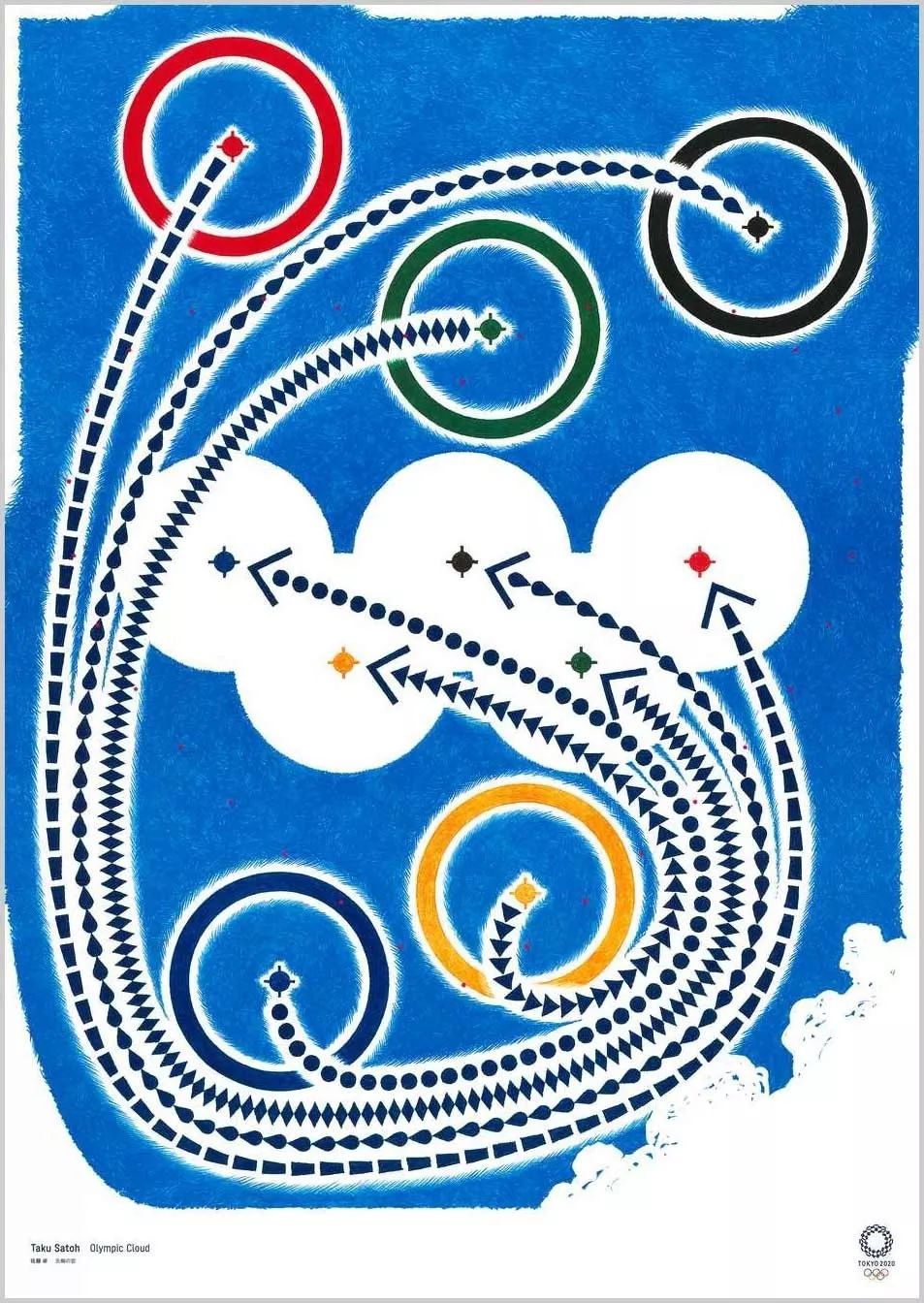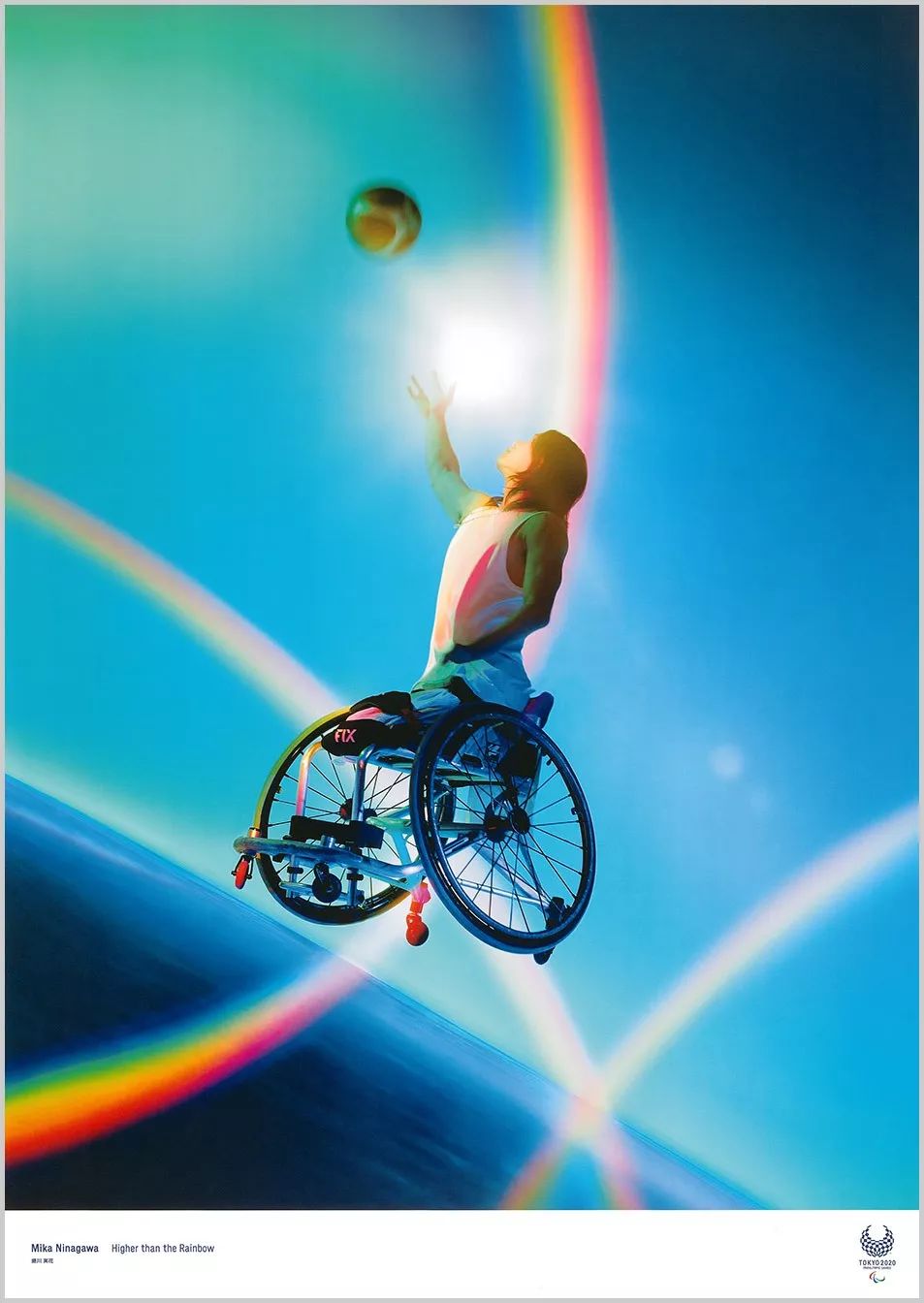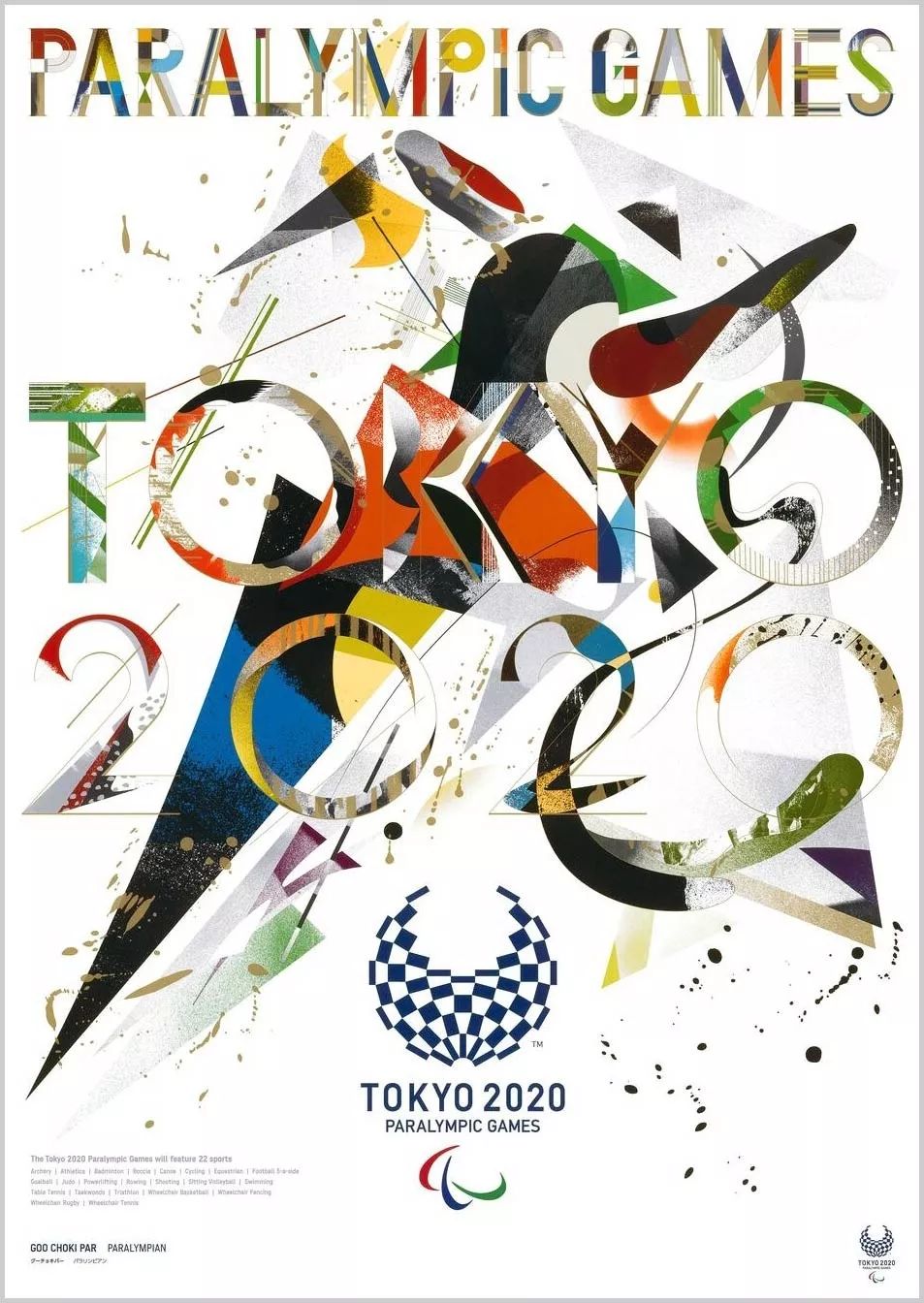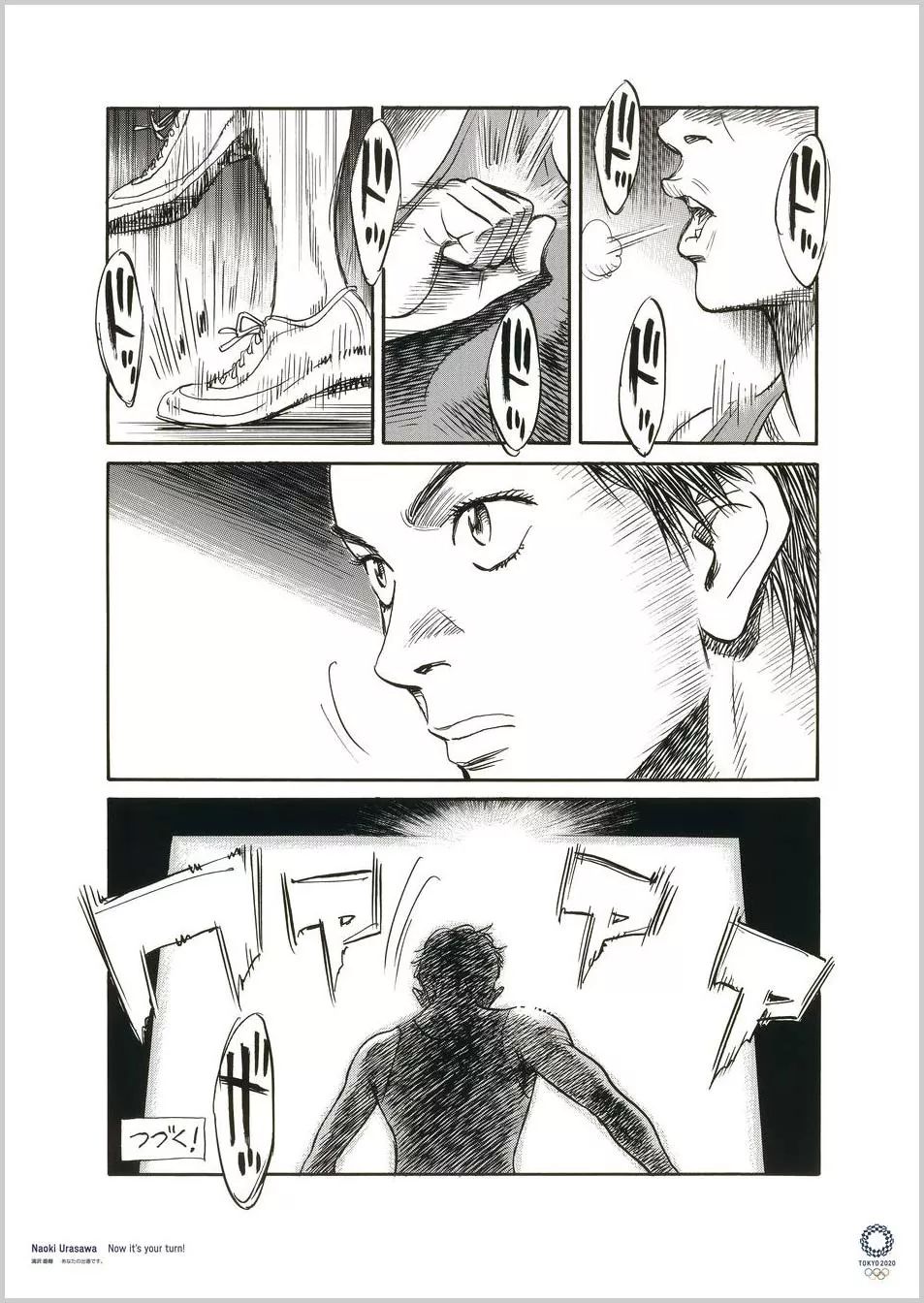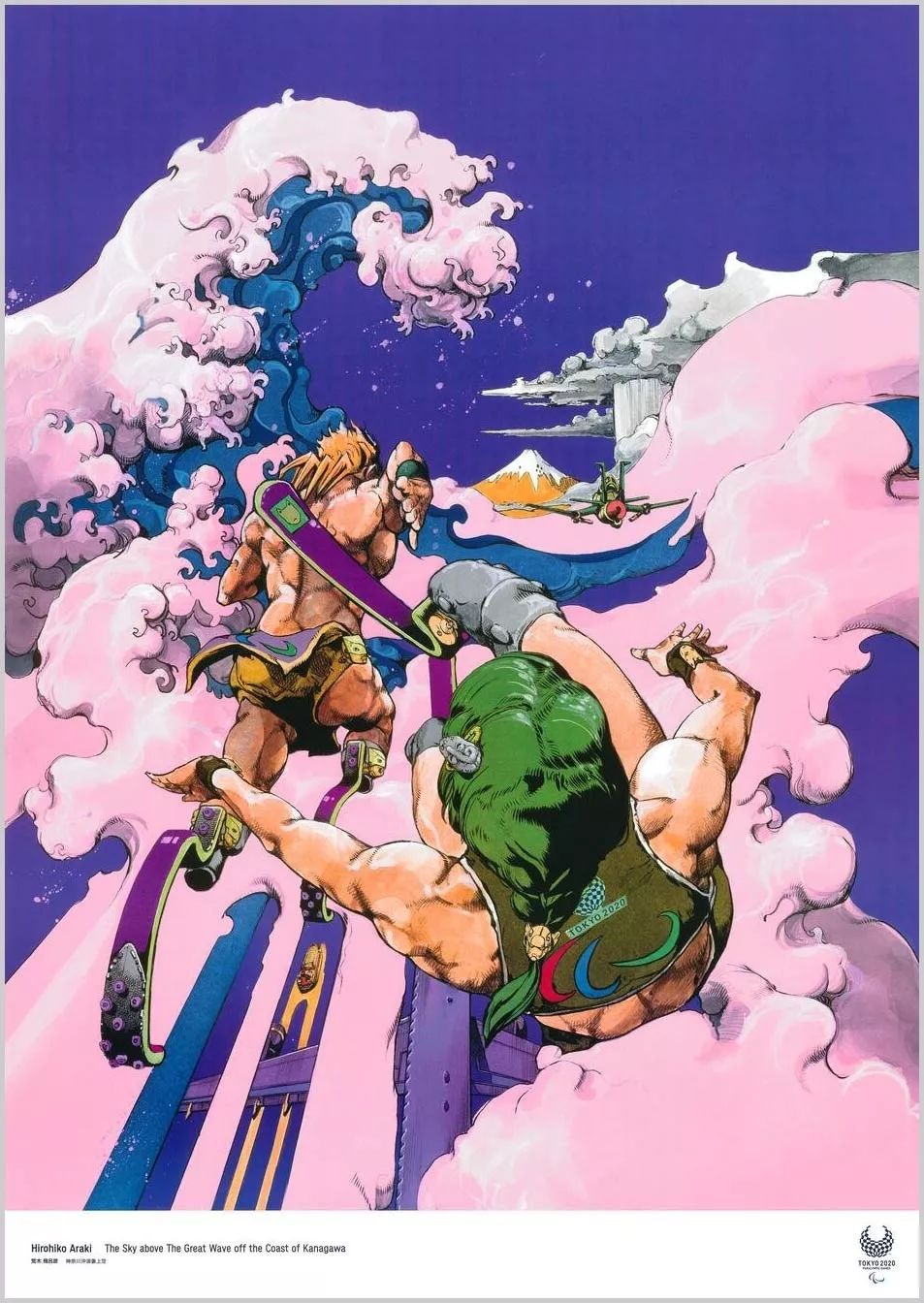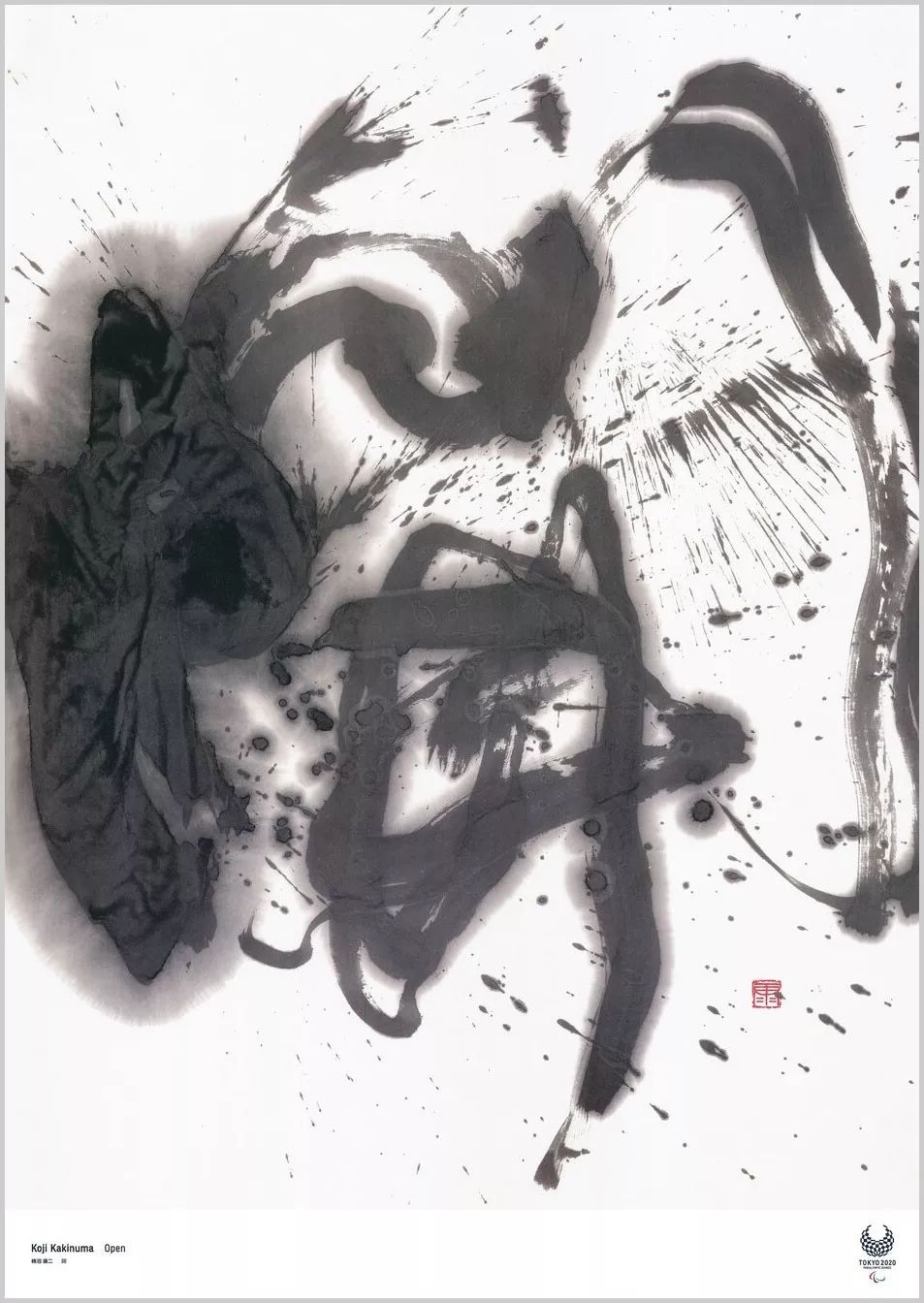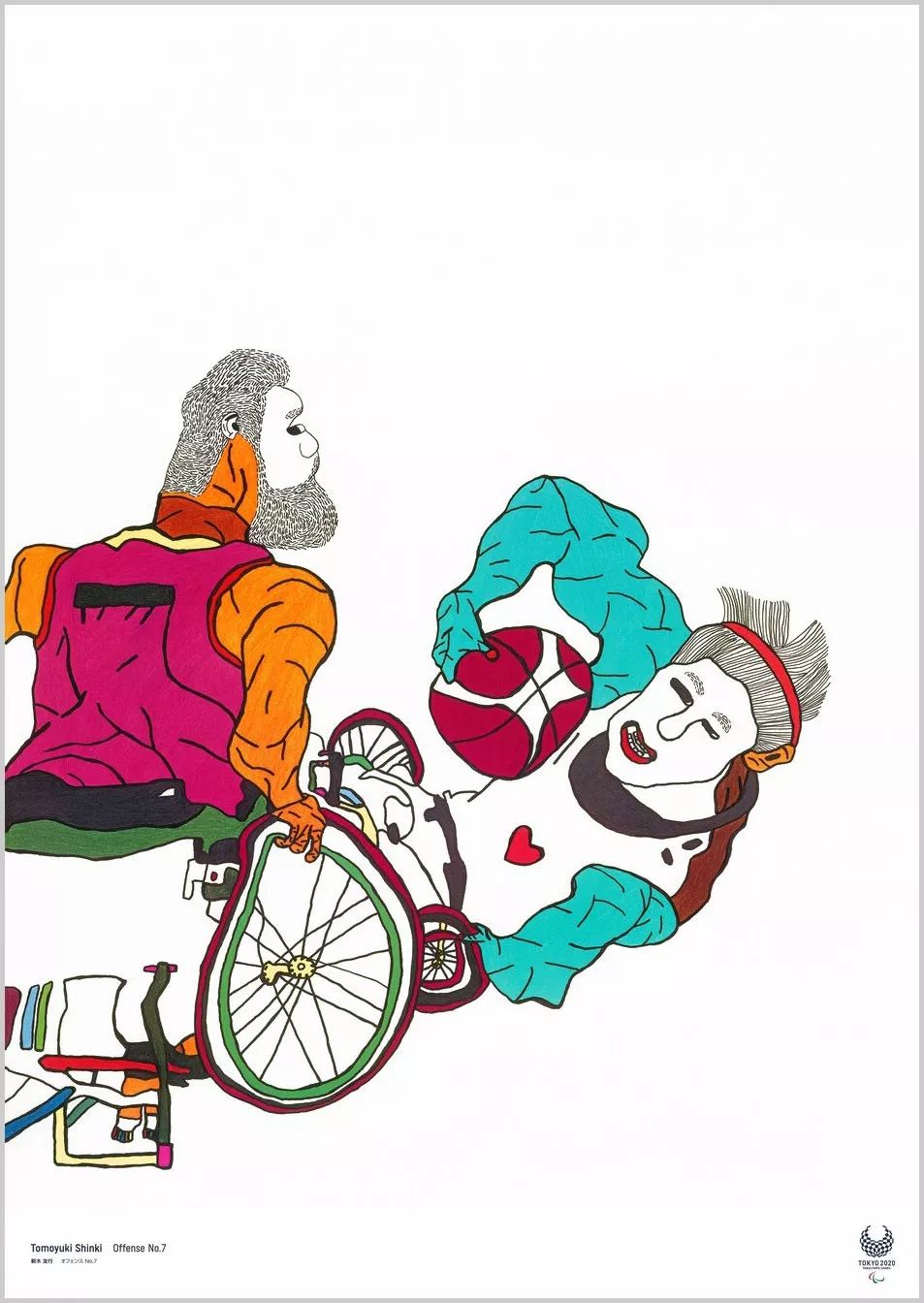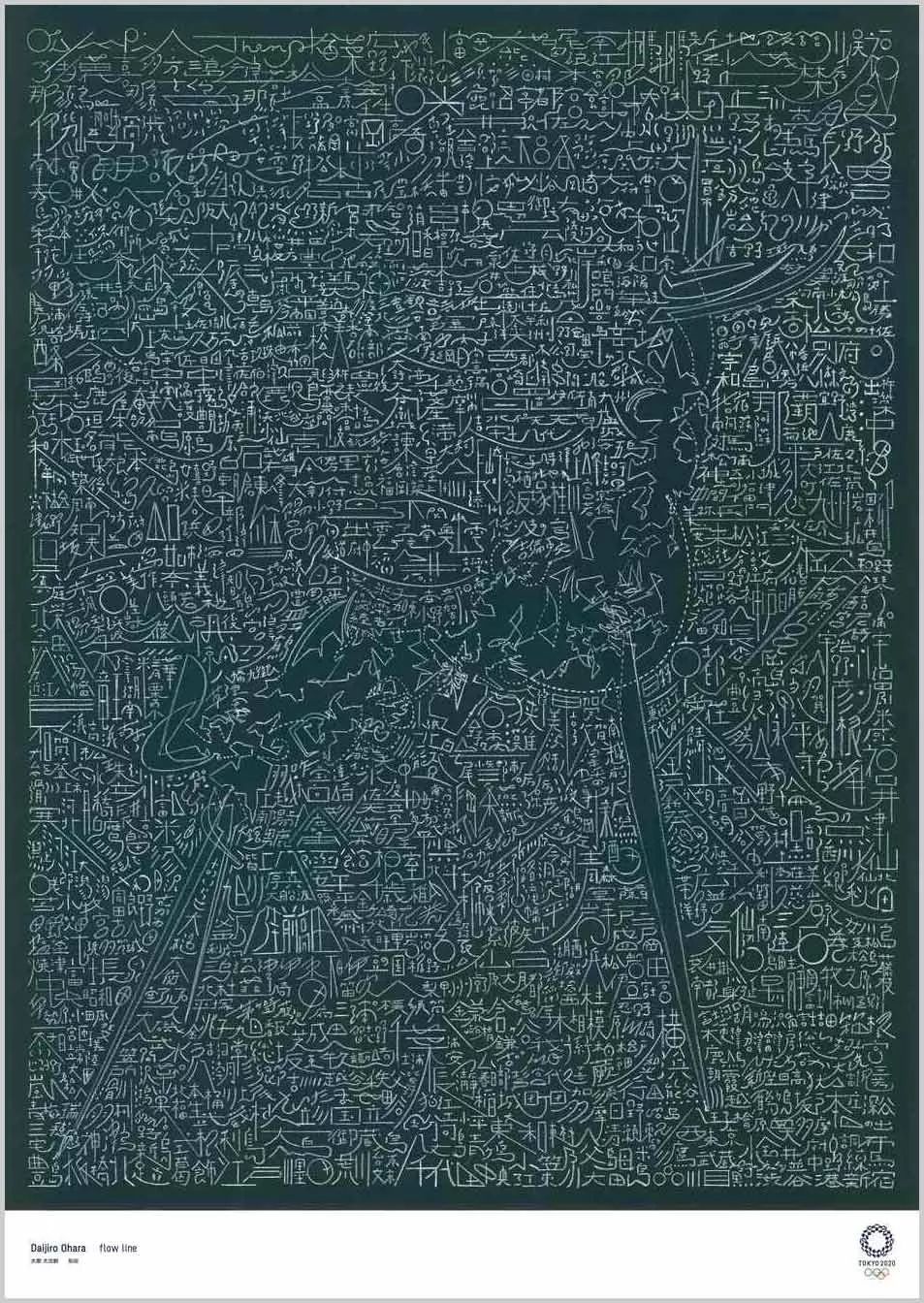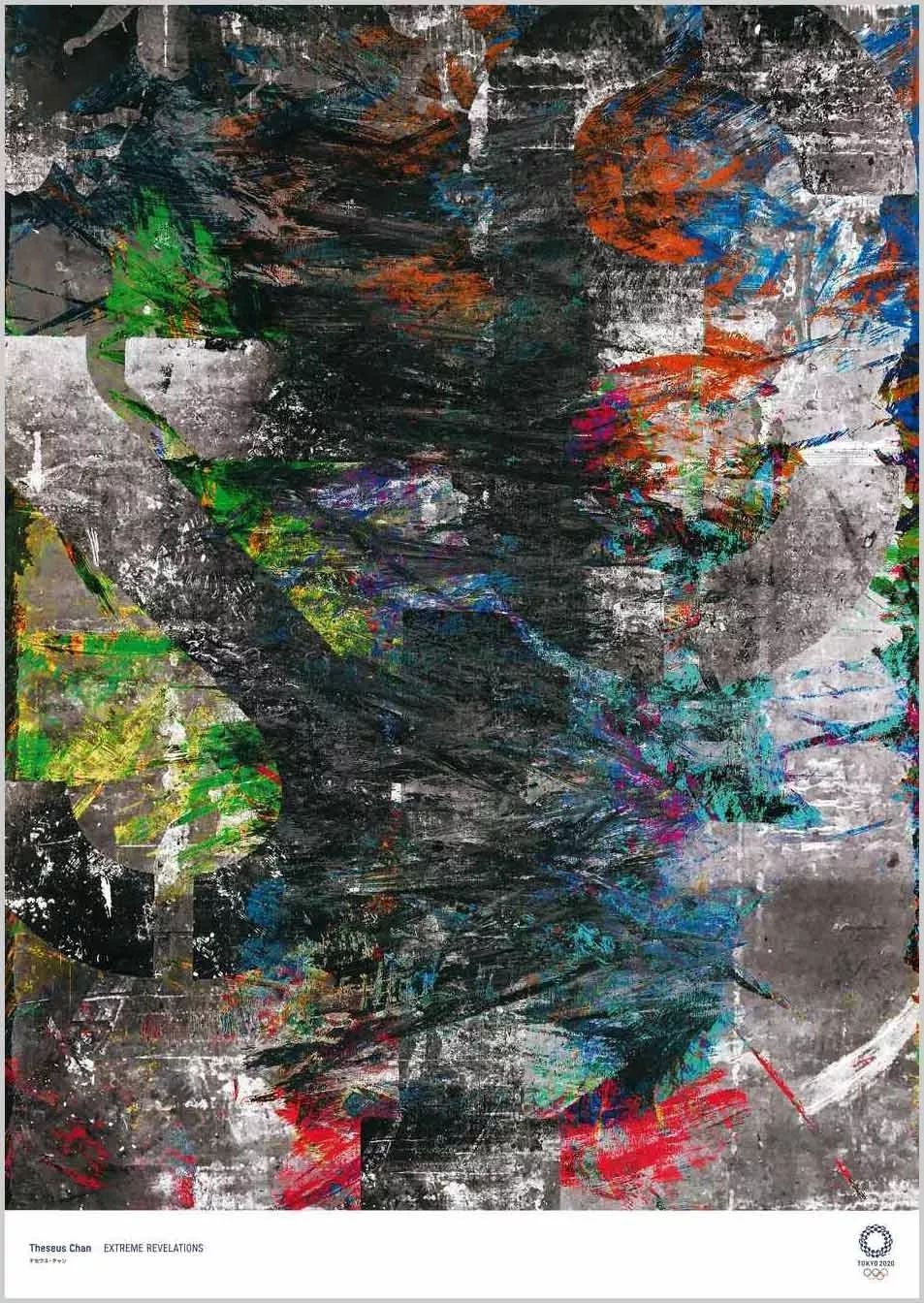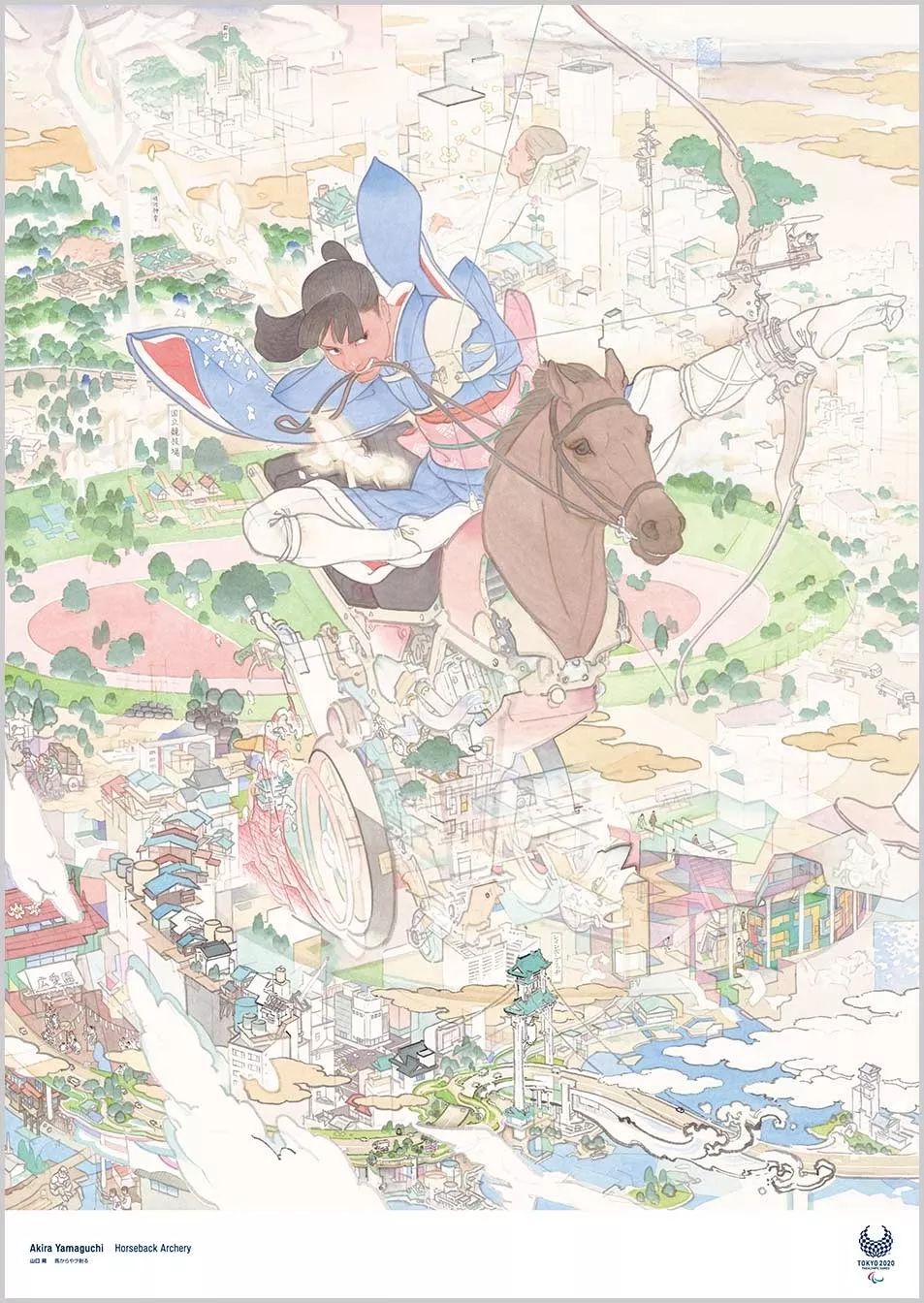
2020东京奥运会新海报公布!19位国宝级大师
如今2020年东京奥运会
已经倒数不到200天!
随着日程越来越近
除了赛事项目与门票开始售卖外
2020东京奥运艺术海报也正式亮相了!
这一亮相可不得了
这次的艺术海报设计阵容可谓空前绝后
聚集了日本19位国宝级艺术家
荒木飞吕彦、浦泽直树、蜷川实花、佐藤卓等等
(这大师阵容....嗯,有看头)
又一次让世界见识了
什么才叫做顶级的日本设计!
而今天!日站君不仅要和大家一起欣赏
这场伟大的视觉盛宴
还要来探究每张海报
背后的故事、灵感来源和设计理念!
那话不多说,咱们这就开始!
野老朝雄(艺术家)
前一阵,艺术家野老朝雄为东奥会
设计的一组具有江户时代特色的
“组市松纹”图案会徽
你们还记得吗?
而这次的海报
野老朝雄依旧运用会徽图案为基础
其中会徽中的“单个”矩形图案大小不一
部分是在计算机上创建的,部分是手工创建的
科技与手工的结合
目地是创建一个“接力棒”
致敬1964年东京设计师
佐藤卓(平面设计师)
海报虽然是静态的
但平面设计师佐藤卓让它在你的脑袋里
“动”了起来
还是以经典的奥运五环为主角
将它们拆解开来
去“创造”出它们新的运行轨迹
不自觉的,令人在思考
它们最终是如何相遇并达到和谐的视觉
蜷川实花(摄影师)
蜷川实花与运动员之间只是简单的按下了快门键
就出现了这幅作品
"残疾人运动很棒"
就是这张海报想表达的意思
荒木飞吕彦 (漫画家)
身为动漫大国
自然少不了动漫能量
著有《JoJo的奇妙冒险》的荒木飞吕彦
也为东京奥运会“献”上了一份自己风格的海报
构图灵感主要来自
浮世绘大师葛饰北斋的《神奈川冲浪里》
艳丽的色彩视觉描绘运动之神
从动荡云海中降落至日本
仔细看会发现常以青蓝色作为象征的富士山
在其手中则成了亮丽的蜂蜜色
喜欢荒木飞吕彦作品的朋友
也一定会发现他藏在画中的彩蛋
福葛发型、石假面头饰
皇后杀手的护腕、黄金体验的发饰等等
完美的将代表作与日本元素合二为一
除此之外另一个漫画形式的海报来自:
浦泽直树(漫画家)
利用有限的页面格数
描绘出少年正在目不转睛地
观赏一场刺激的比赛的场景
分镜头的细节
展现出了运动赛事热血与紧张感
而最后一句「现在,轮到你了!」
更是振奋人心
也影射了东京奥运会即将来临
每个人都怀揣着激动的心情
金泽翔子(书法家)
除此之外,这次汉字书法也荣幸的
入选了东京奥运官方海报:“翔”与“开”
其中一个:金泽翔子的“翔”
是希望运动员的热情飞跃东京之上
并可以触及全世界
而“翔”字上耀眼的光芒代表了运动员的能量
而且“翔”字是
在覆盖着金箔的地面上书写的
凸显了日本的优良工艺
利用这样的特殊方式制作海报
更是传达了深度
让东方传统媒介站上了世界的舞台
另一个则是:沼康二(书法家)的“开”字
沼康二想象奥林匹克和残奥会的运动员
每天都在努力
并向自己说:“Open,Open,Open!”
他就这样在纸上不停的写
直到感觉完全“Open”时
他更希望来自世界各地人为这项盛大的节日活动
以及支持奥运会的每一个人齐聚一堂
Chihiro Mori(艺术家)
看起来像条形图的高楼
看起来像肠子的连接点
用“超越曲线”来表现奥运力量
GOO CHOKI PAR(平面设计师)
人类对不断进步的渴望
消除了身体上的限制、消除了障碍
并跨越了民族和性别的界限
作品的主要主题是向前迈进的个人
手臂大胆摆动,双脚全力撞击地面
这种原始的运动体现了
所有残奥会运动员朝着更美好的未来前进的决心
Tomoyuki Shinki(艺术家)
Tomoyuki Shinki选择篮球为主题
因为观看篮球比赛本身令他很兴奋
所以他选择了明亮的色彩
去凸显玩家的全力以赴
艺术家希望的是
观众们无论是心情愉悦还是情绪低落
都会感受到运动员的勇气
以及运动项目的吸引力
大原大次郎(Daijiro Ohara)(平面设计师)
这个世界上有无数的线条相交
有时彼此缠绕在一起,有时变得松散
正是这些线构成了图像
而这张海报代表了奥运圣火
在2020年奥运会期间
从希腊到东京的预期移动路线
以及在日本进行火炬传递过程中的800多个城市
小池智子(艺术家)
作为动物,每个人以完全不同的感知来把握世界
我们通过自己的热气球看到世界
没有一样东西是相同的
小池智子一面对奥运会有着祝福
一面为新生态系统有着期待
陈修(Theseus Chan)(艺术总监)
Theseus Chan的海报
不得不提的是:滑板运动
而它的标签是:反叛
它有自己的语言,它在不断地发展
是艺术、设计、时尚、音乐甚至手势的综合
Theseus Chan的思考是:
滑板磨痕被颠覆为画笔笔触
从内部爆发出的极其明亮的色彩
彰显的正是青春和无耻的精神
还有几乎看不见的数字和图形的神秘倒置
在质疑这世界上是否有既定的顺序
Takashi Homma(摄影师)
摄影师Takashi Homma的《东京の子供》
以小孩为主
意在奥运不仅是运动员的盛宴
更是跨越儿童到老人不限年龄的活动
是整个国家充满希望和难忘的时刻
Philippe Weisbecker(艺术家)
当Philippe Weisbecker第一次看到
新奥林匹克体育场的模型时
得到了他的灵感
画了许多草图、经过几次修改
最后运用具有代表性的宣纸
画出了他自己想象的体育场
薇薇安·萨森(Viviane Sassen)(摄影师)
薇薇安·萨森想描绘的
是有趣、是游戏的欢乐
与此同时暗示奥运会文化多样性和民族多样性
彩色墨水的大“点”指的是奥运会官方徽标的圆圈
除此之外,还有三位画家
用自己的艺术感官描绘了心中的奥运
大竹伸郎(画家)
克里斯·奥菲利(艺术家)
Akira Yamaguchi(画家)
看了一圈发现,虽然海报的风格各不相同
但2020东京奥运会/奥运精神
是每一张海报的灵魂
艺术家们用自己擅长的方式
表达自己心中的奥运
是祝福、是期盼,各有寓意
不得不说,日本作为设计大国
再一次为我们上演了一场
空前的视觉盛宴
在这样骄傲的时刻
19位国宝级艺术家
站在世界的舞台上用作品告诉所有人
什么才是创造的力量!
什么才是想象的无极限!
什么才是顶级的日本设计!